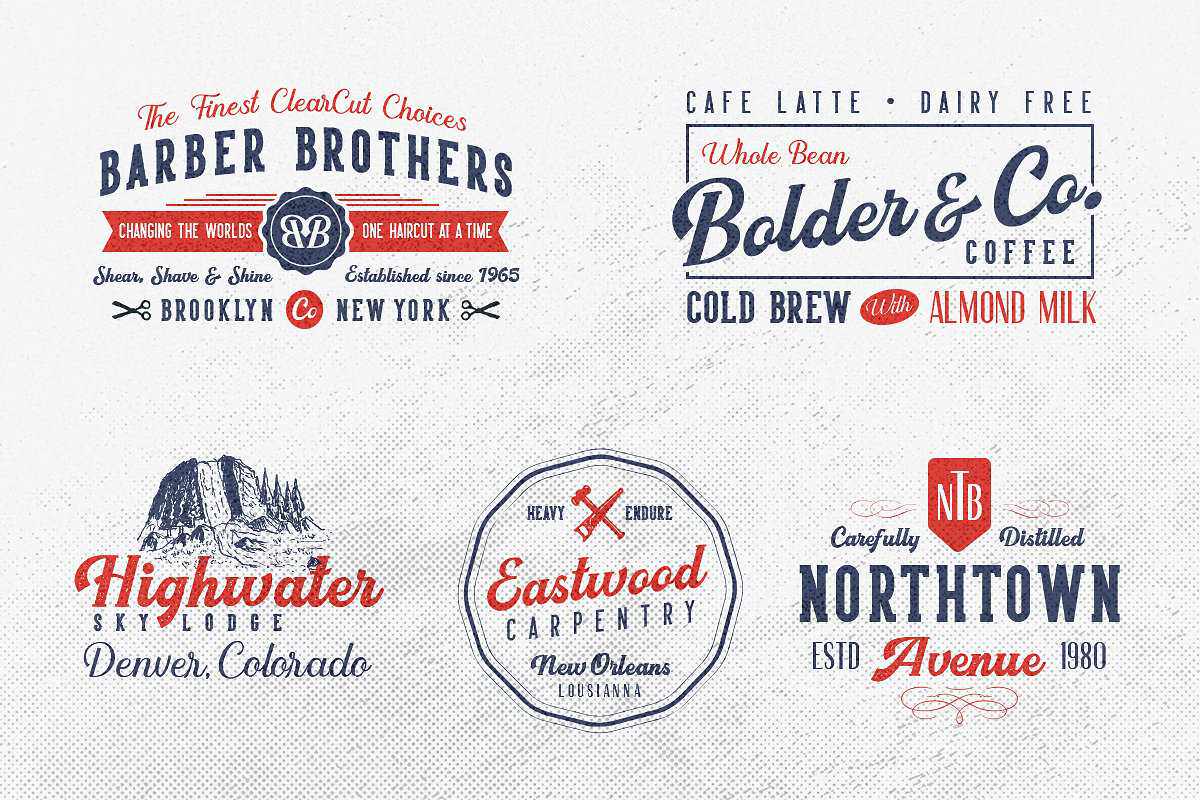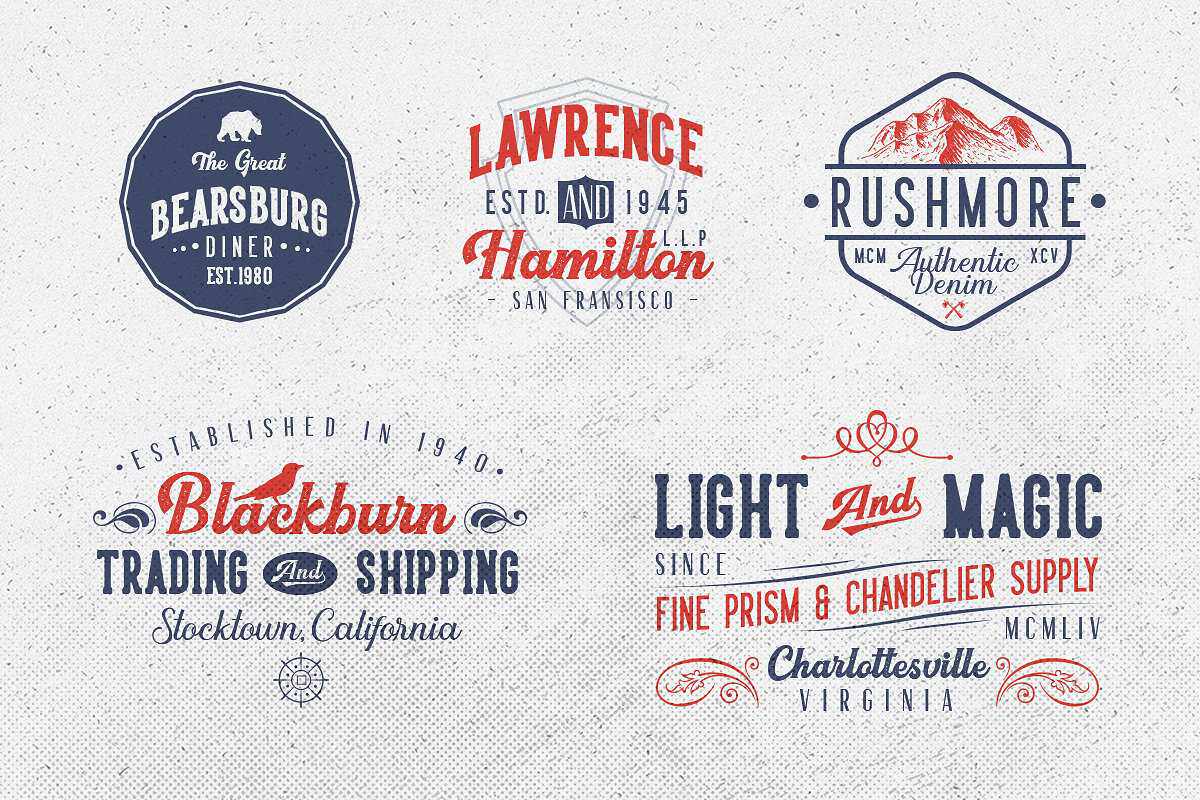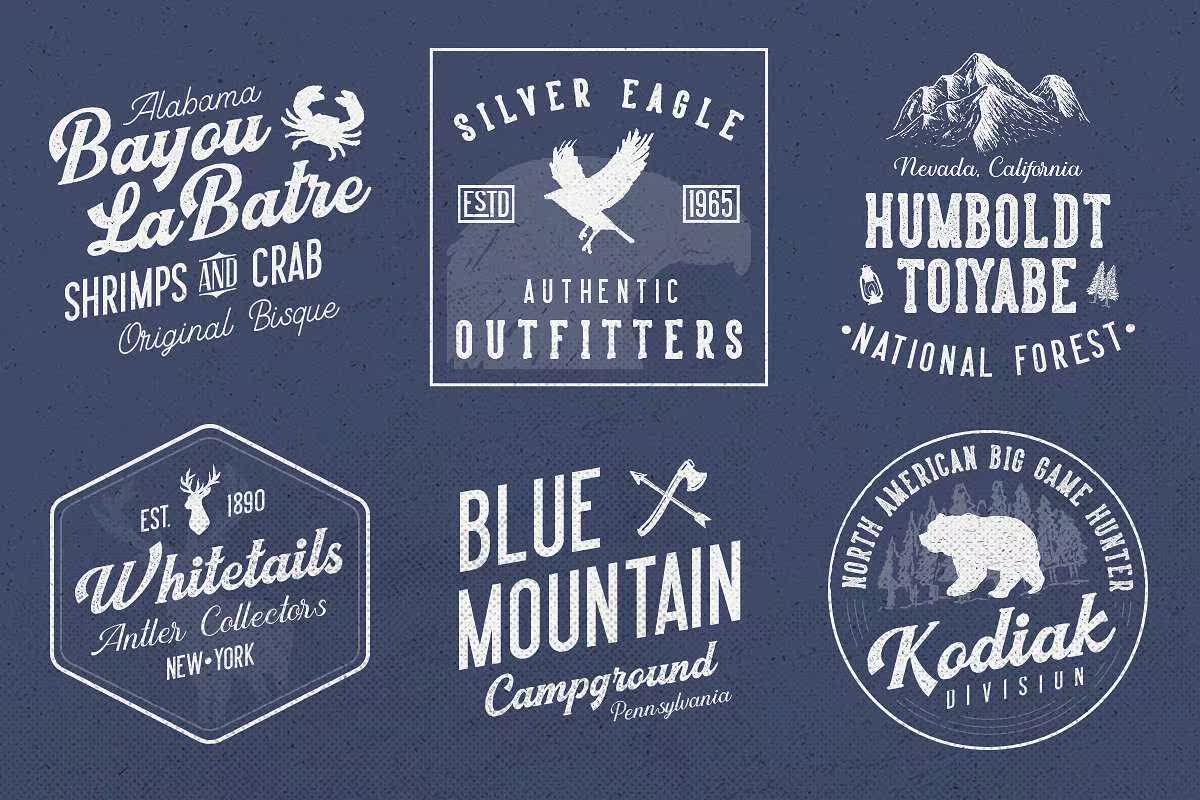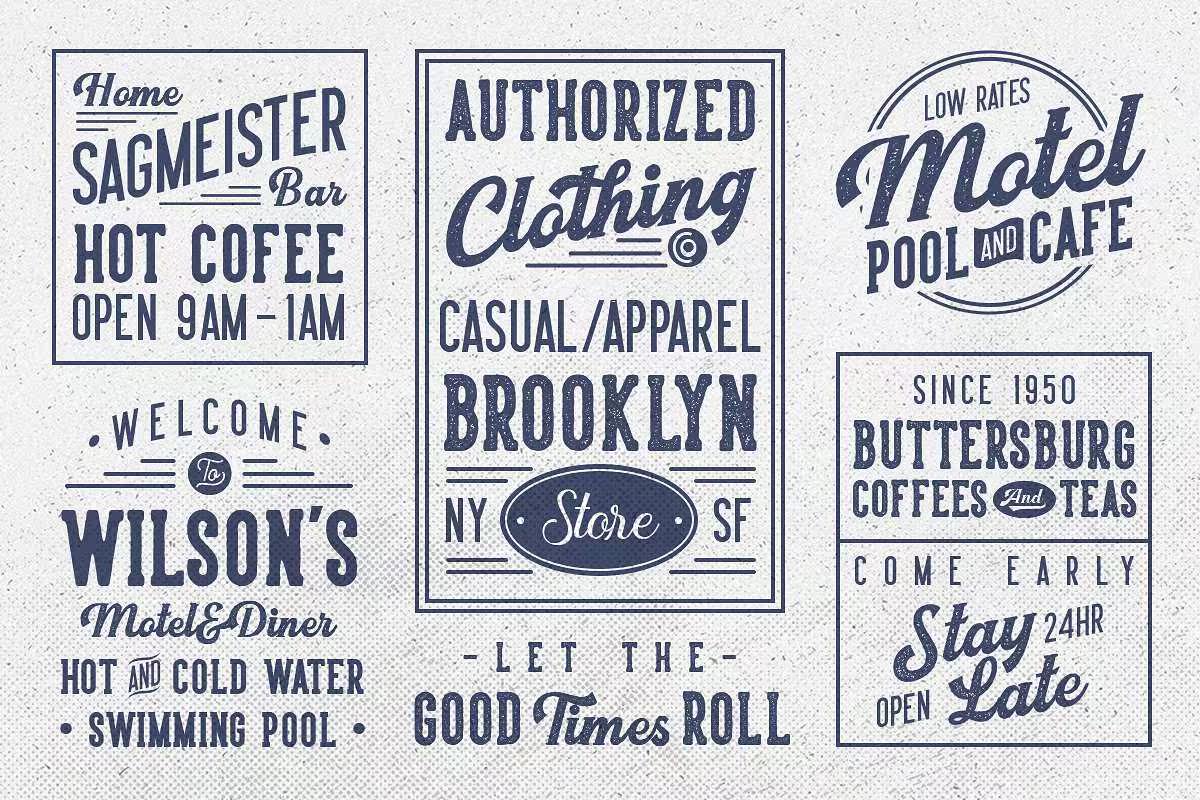
HarseyTypeToolbox。我们创建的最受干扰的设计产品之一。该产品包括任何样式的SCASScript、sans、serif,还包括DINGBATS、,流行语和广告均采用字体格式。该产品还包括20个预先设计的标签/标签,这些标签/标签的内容是非法的,因此您可以在Asec中简单地创建自己的产品。该产品的特点是更专业,您可以使用和组合这些字体,使其与其他。HarseyTypeToolbox完美匹配。这是我们创建的最新设计产品之一。该产品符合任何样式这些脚本、sans、serif和包括蝙蝠、流行语和广告在内的所有字体均为正版格式。此产品还包括20个预降级/标签,这些标签的版权是非法的,因此您可以在自定义C中轻松创建自己的产品。此产品更专业的特点是,您可以使用这些字体并将其组合在一起。